字体设计的重点是要符合主题的要求。一个标志、一个商品品牌都有其自身的内涵,将其更准确地传达给受众,是设计的目的。所以我们需要根据不同的受众需求做出合适的字体,不能随意地设计。一般情况下,女性用品的设计使用的字体比较柔美;男士用品的设计使用的字体则显得刚硬;比较有历史背景的字体则显得比较古朴。
柔美型
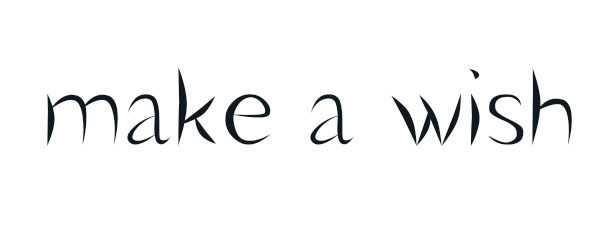
这类字体给人的感觉优美清新,线条流畅,有一种柔美之感。在一些化妆品、饰品以及日常生活用品中常会用到这种字体。字体视界中的代表字体有印品芷兰体。 这款字体粗细变化自如,粗若螳螂肚,细若幼鼠尾;且柔中有刚,很符合女性的一些特质。
力量型
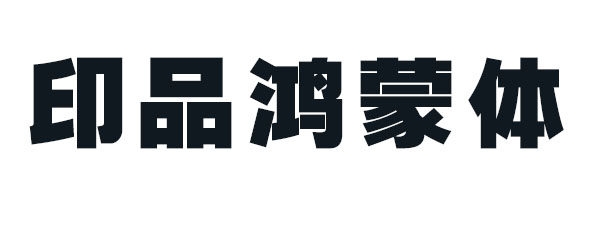
这类字体气势突出,有很强的视觉冲击力,个性张扬,节奏分明,用于表现强烈的信心和勇气,能体现出凝聚力和号召力,给人一种视觉上的震撼感。印品鸿蒙体这款字结构严谨端庄,字形饱满,字体间距布局均匀讲究,整体美观又大方,整体风格刚劲有力而又不失俊儒之风;笔画之中蕴含古朴沉厚端凝之势。在主标题上有很大的应用空间。
趣味型
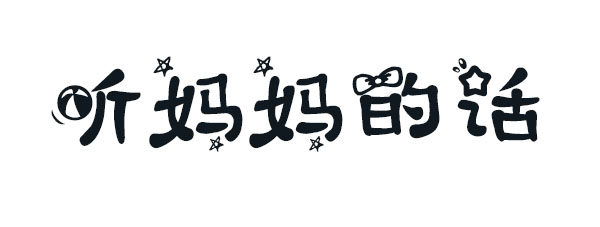
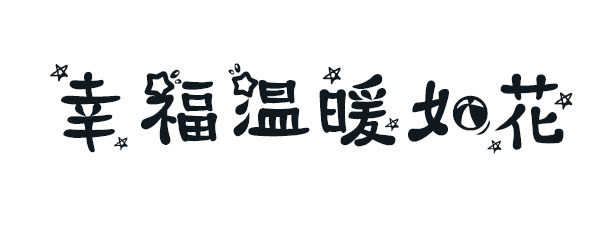
这类字体整体偏可爱,在一些儿童产品中比较常见。该字体将儿童喜爱的皮球蝴蝶结等元素融入到字体中,更能体现出孩童的活泼好动。
古朴型
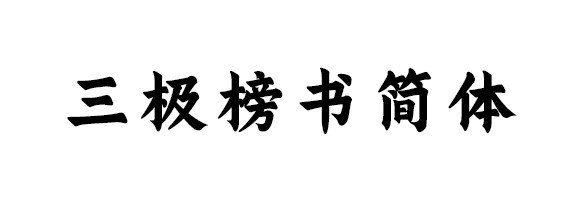
这类字体在一些比较有历史背景的产品中较为常见,具有一种信赖感和说服力。古朴型字体主要以书法字为主,洒脱大气,富含古韵。三极榜书简体字体以传统楷书大字为结构雏形设计,笔画豪迈雄伟,笔墨中正,字形雍容大气,厚重沉稳,极富艺术感染力。适用于各类传统习俗的包装和宣传设计及书法作品排版标题、招牌设计。